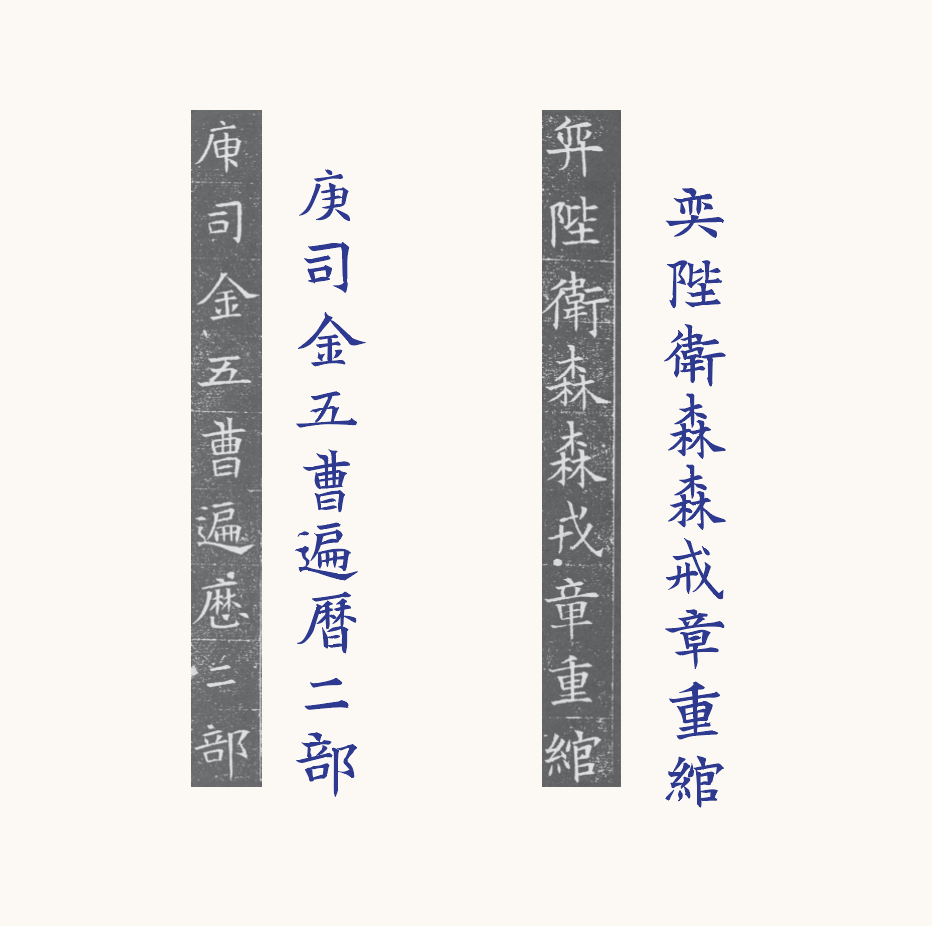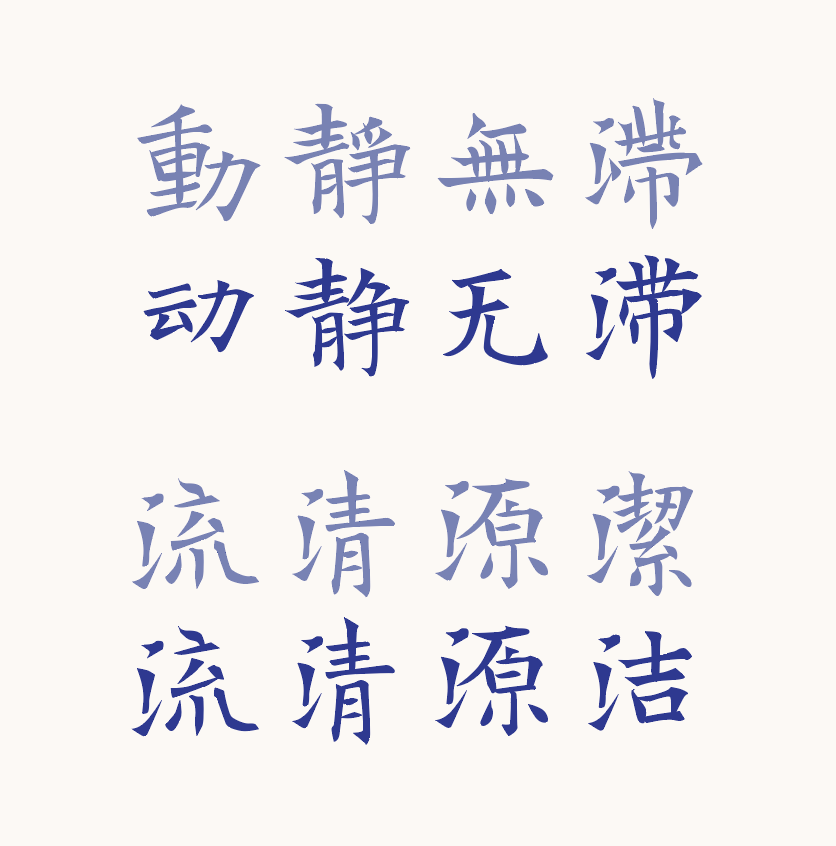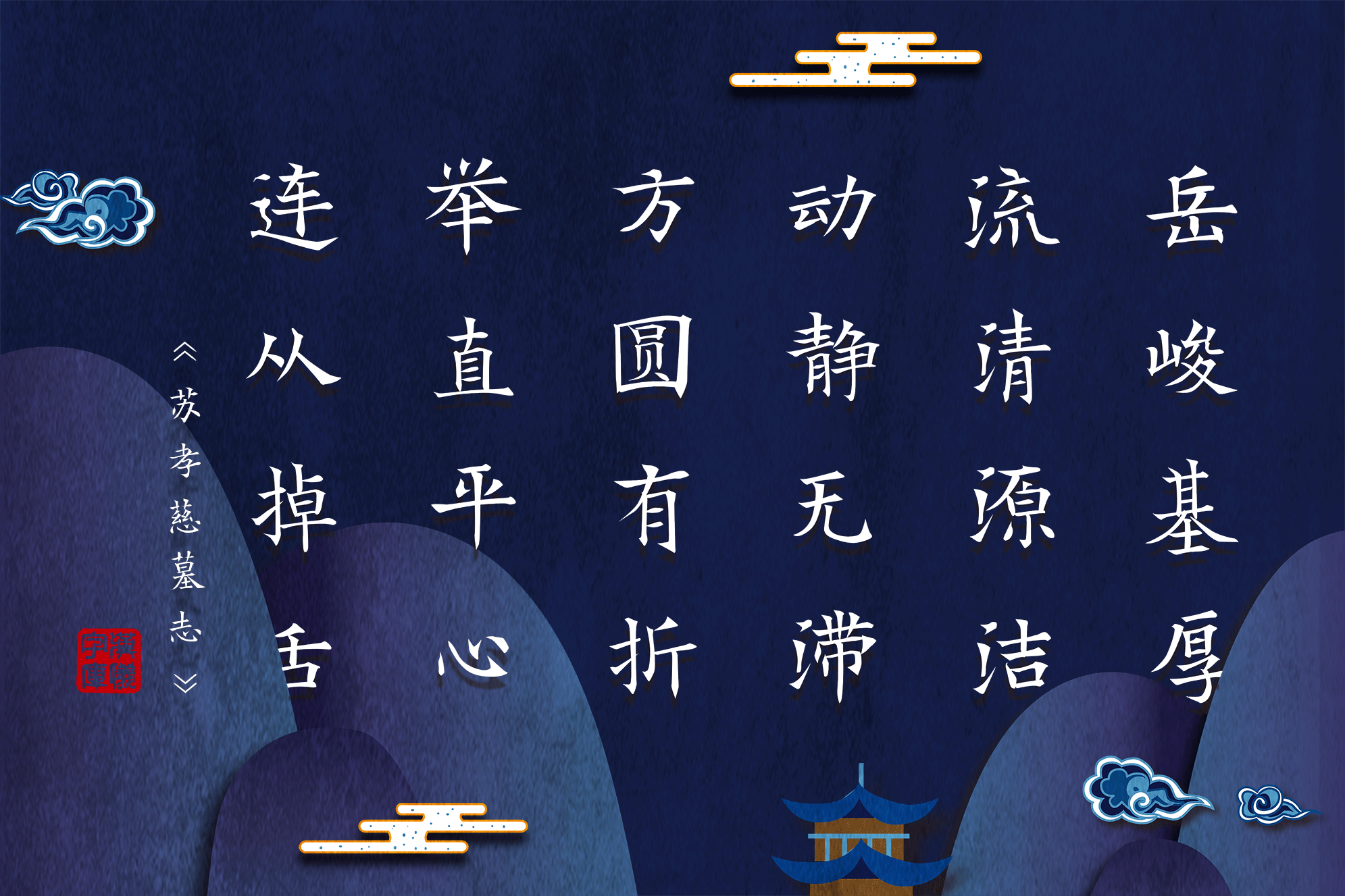
汉仪新蒂苏孝慈碑字体介绍,汉仪新蒂苏孝慈碑字体设计思路
历史渊源
汉仪新蒂苏孝慈碑,是根据1887年在中国陕西蒲城县出土的苏孝慈墓碑铭文而设计的。
汉仪新蒂苏孝慈碑字体风格呈现了南北朝时期到唐朝书法的过度,可从中窥探唐朝楷书,特别是欧阳询楷书的一些风格。
字体特点
汉仪新蒂苏孝慈碑的书写结构严谨、运笔纯熟,繁体和简体均很好的保留了苏孝慈墓碑铭文内敛庄重的气质。